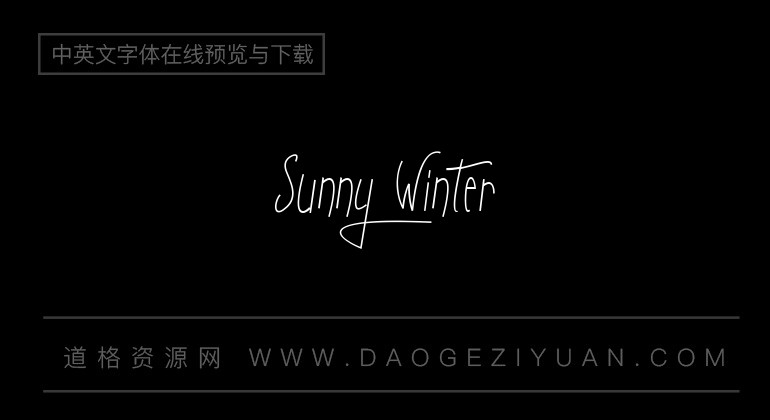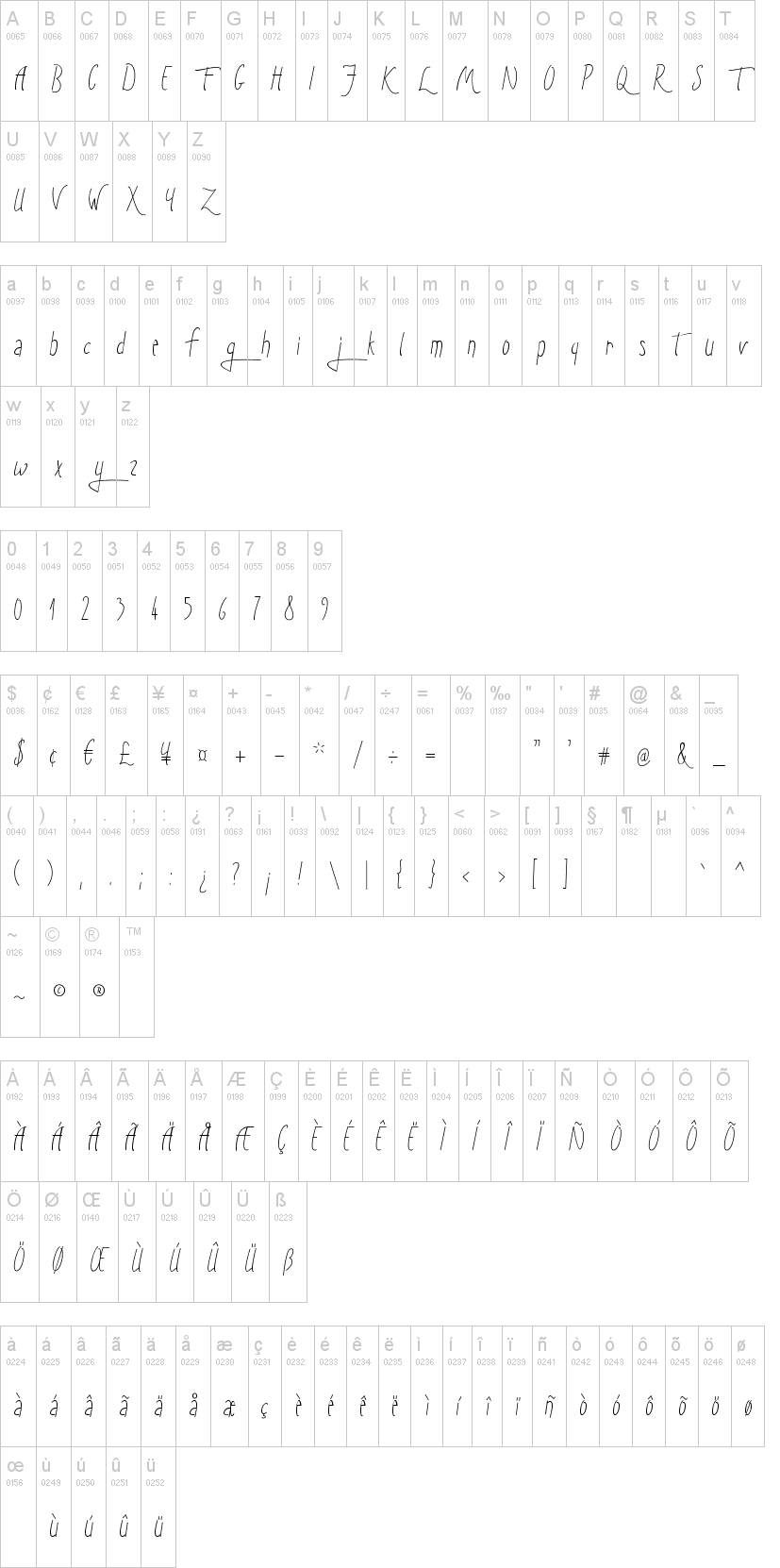
Sunny Winter
Sunny Winter 字体是一款新颖的活泼字体,它拥有轻松、温暖的感觉,适合用于日常印刷、广告、商业活动等场合。它的字体特点是细节精致,曲线流畅,笔画宽度统一,字母间距合理,使用起来非常舒适。它的特色是温暖的色彩,可以提升文字的视觉效果,让文字更加有趣,更加有魅力。
Sunny Winter是一款非常不错的手写艺术字体,具有很好的视觉感,适合于文化类的宣传设计、商业类品牌的广告和产品包装设计以及个性化文字排版等较多场景。